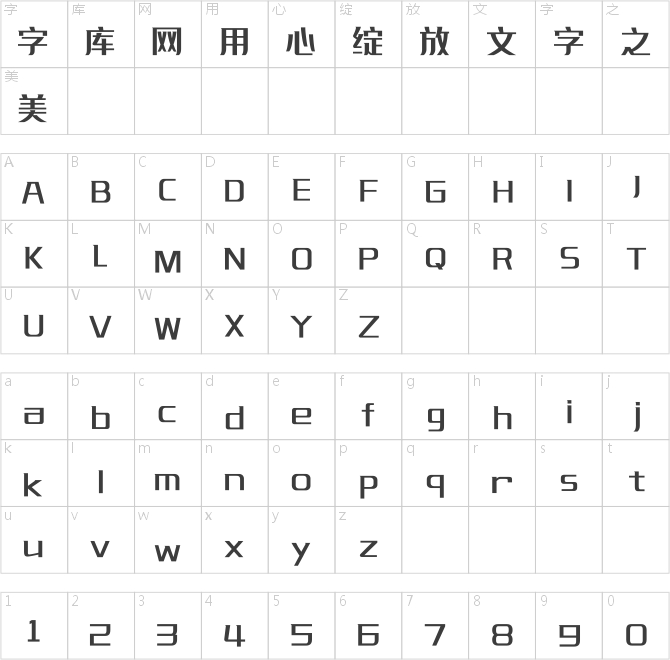
字體名稱: 上首寬云體
上首寬云體,字體風格穩(wěn)重呈方塊形,字體筆畫豎折處細節(jié)處理,是此套字庫的亮點。字庫整體特征堅硬、有力,具有現(xiàn)代、國際化的指向性,適用于搭配標志、廣告標語、商業(yè)廣告等高端屬性。
上首寬云體字體字庫是一款讓人賞心悅目、百看不厭的中文字體,適合各類廣告和產(chǎn)品包裝設計應用,字體大小2.34MB,格式為ttf字體,上傳用戶是上首造字,作者/版權方為上首造字